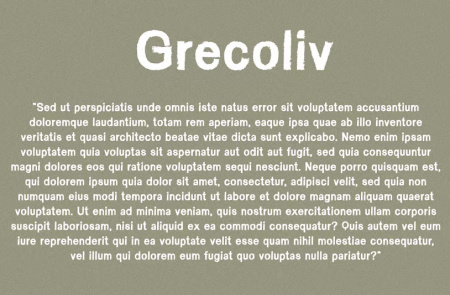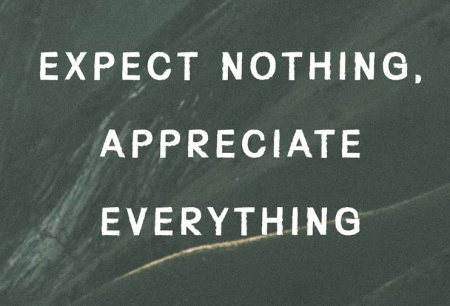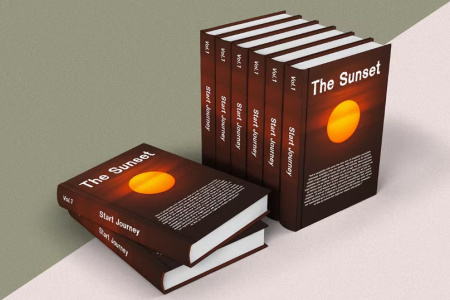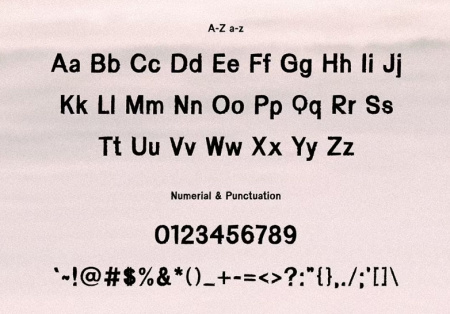
Grecoliv یک فونت براش بافت مدرن و خیره کننده است که به راحتی می توان آن را بدون توجه به مناسبت با مجموعه ای فوق العاده بزرگ از پروژه ها مطابقت داد! این فایل شامل حروف بزرگ، کوچک، اعداد، علائم نقطه گذاری، نمادها است و از چند زبانه بودن پشتیبانی می کند. دانلود رایگان فونت انگلیسی براش Grecoliv برای پروژه های مختلف مانند بسته بندی، ارائه، لوگو، سرفصل، حروف، پوستر، نام تجاری، نقل قول، عنوان، عنوان مجلات، طرح بندی وب، تبلیغات، دعوت نامه ها، طراحی بسته بندی، کتاب ها و تقریباً هر طرح خلاقانه ای عالی است. برای دریافت این فونت انگلیسی رایگان از سایت gfx به ادامه مطلب مراجعه کنید.
فونت انگلیسی براش Grecoliv
فونت انگلیسی با تم براش Grecoliv
• نام فونت: Grecoliv Brush
• وزن قلم: معمولی
• حروف بزرگ
• حروف کوچک
• اعداد و علائم نگارشی
• پشتیبانی از چند زبانه (مکمل لاتین + لاتین Extended A)